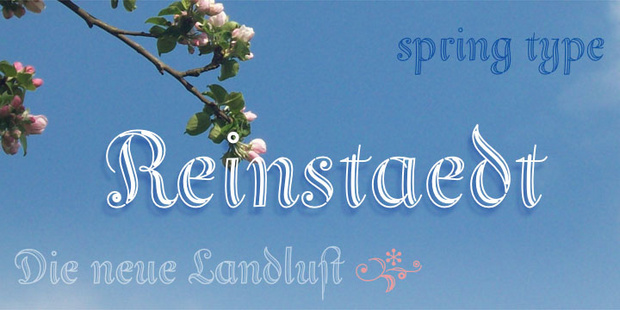
Typo gesucht im Landhaus Stil (Romantik aber lesbar)
Corinthia passt schon ganz gut :-) Merci!
Fallen weitere ähnliche Fonts in der Richtung ein?
Dann leg ich mir mal einen Ordner von Lieblingsfonts aus der Serie an :-)
Ich schreibe Dir jetzt einfach mal ein paar kalligrafische/handschriftliche Fonts auf, die mir so in den Sinn kommen. Ich habe nicht bei allen im Kopf, wo sie zu bekommen sind, da müsstest Du dann mal suchen. Stephanie Marie (Veer?), Ruth (Veer oder P22), Alpine Script (MyFonts?), FS Sammy (Fontsmith) und Creamy Script (MyFonts). Wenn mir noch mehr einfallen liefere ich sie nach. :-)
Es wird kalligrafisch bei mir. Jede Menge Inspiration – meine Federn rufen. Das Schönste: Es macht richtig Spaß! Ein Türschild ist doch was sehr Individuelles, von daher liegt hier meine Herausforderung.
Die Handwritten-Abteilung bei MyFonts hat auch einige nette Variationen und Inspirationen für die Wunschlettern.
Ich kaufe ein D und psssst, wäre da noch ein S? ;-)
Hi, die Schriftart von Posting #4 sollte die Edwardian Script sein.
Die finde ich sehr sehr schön ;)
Wobei die eher so ein bisschen zu Barockem Ambiente passt...